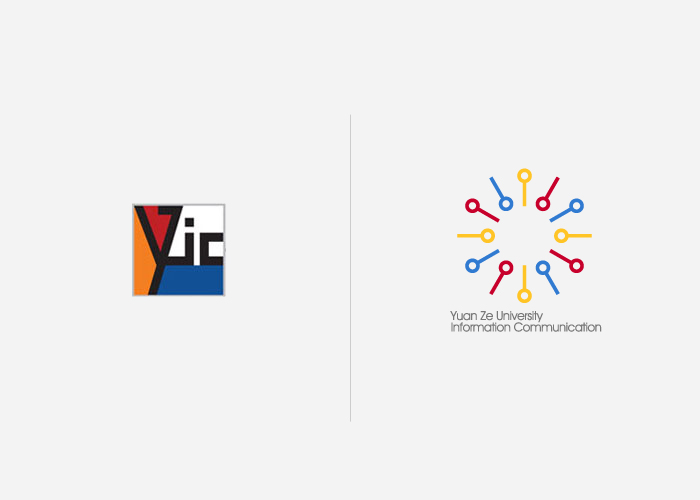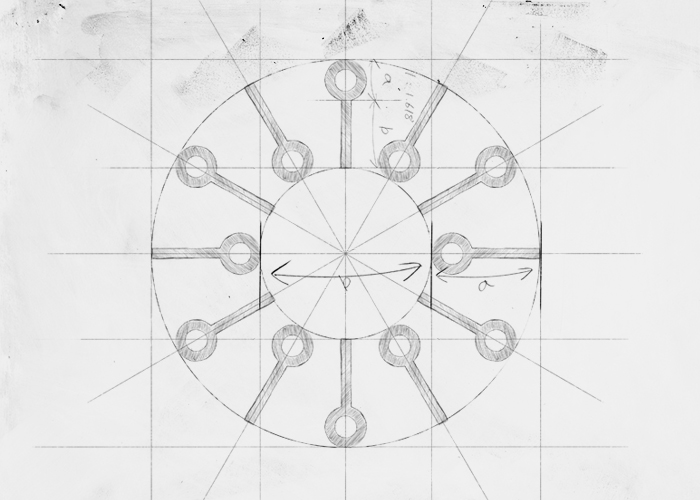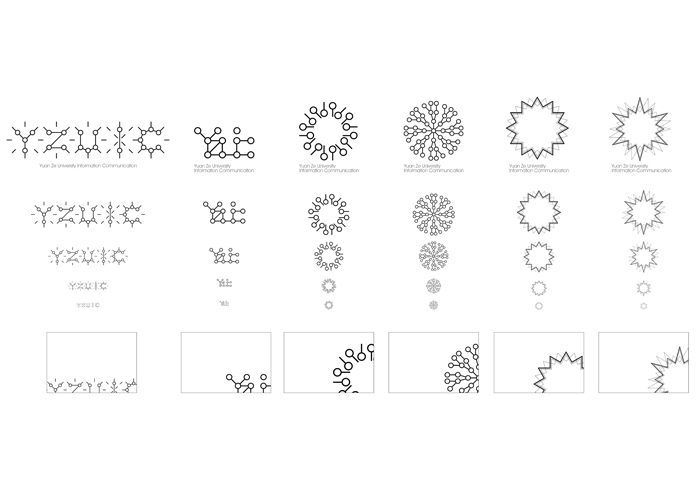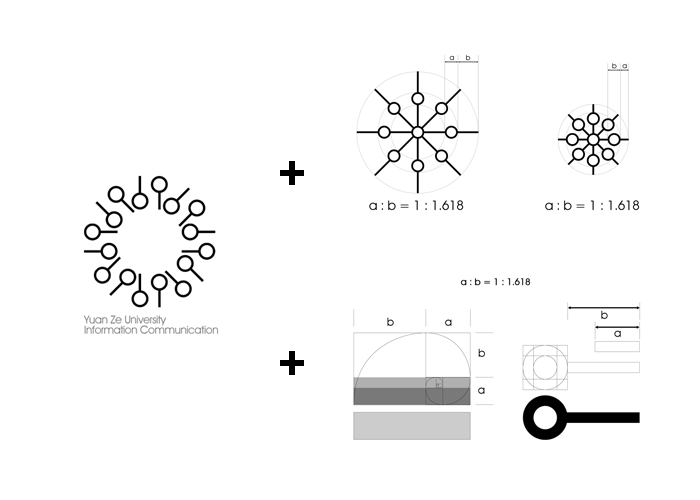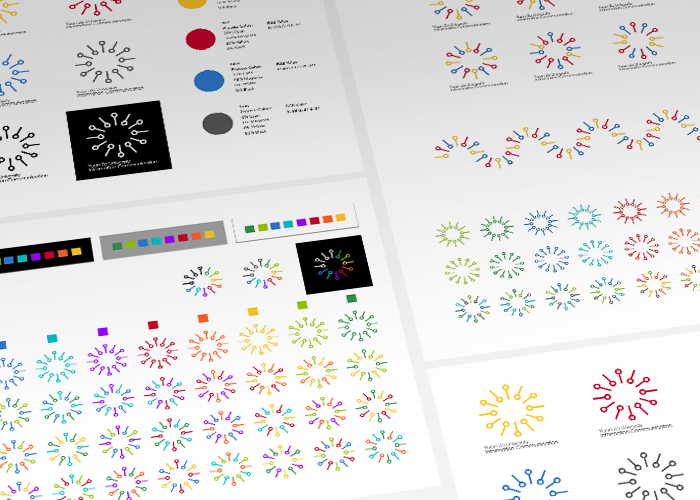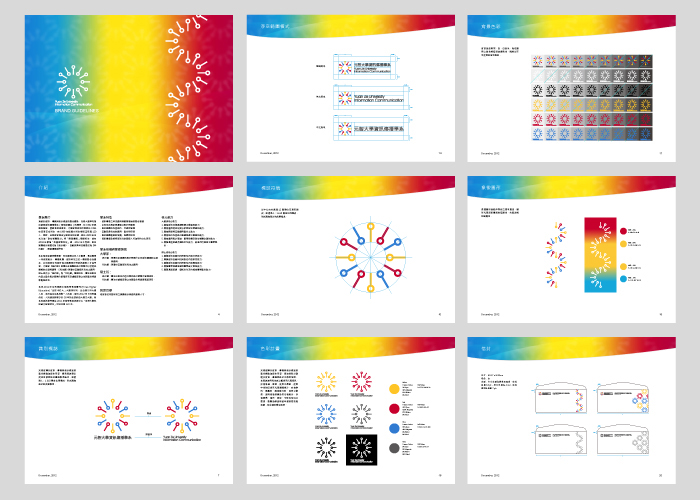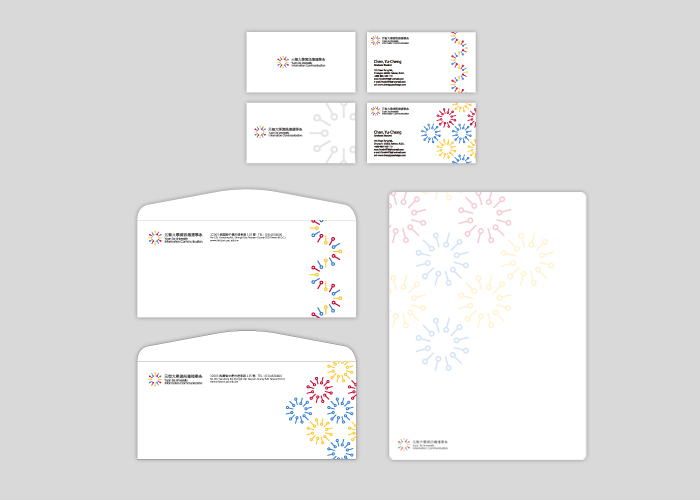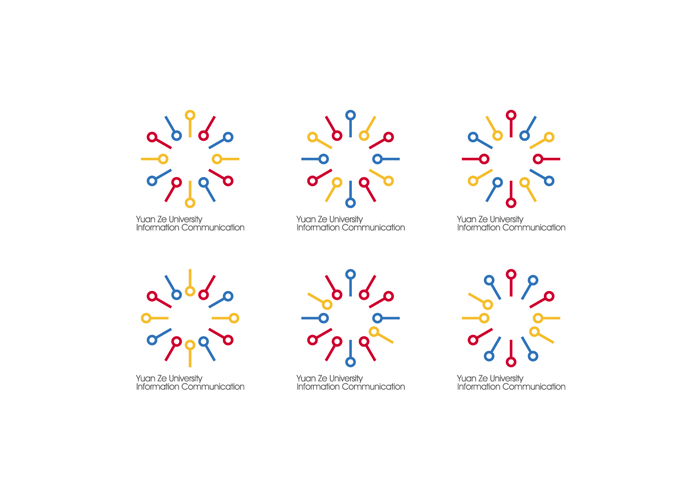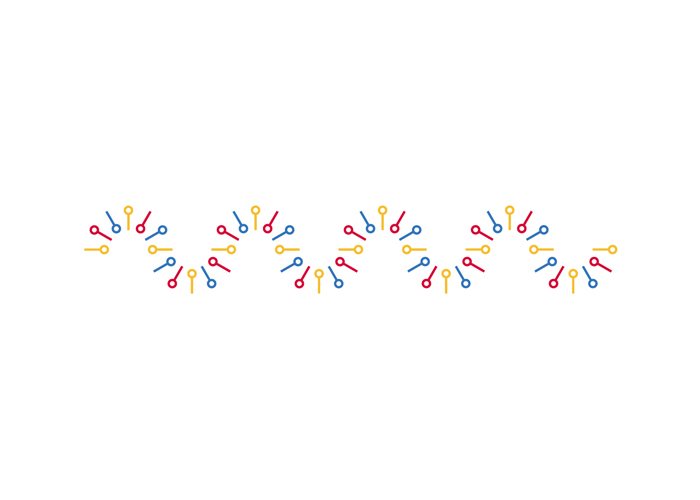
元智大學資訊傳播學系動態商標設計
設計方法與理念:
本創作利用時限性、循環、非固定循環與靜止四種不同時間表現形式,來呈現企業標誌理念。 本創作研究將依照Balmer (2006) 企業識別6Cs概念,分析元智大學資訊傳播學系之理念,標誌設計針對資訊、訊號、傳播抽象概念來發想,識別標誌便以資訊符號與數位傳播概念結合,以結點連結、結點延伸、線條來表示資訊符號之概念,並運用形態、造型、色彩、字型、比例與構成、肌理元素設計。在基本元素構成中,元素的厚度取自於鸚鵡螺殼的結構之比例,標誌的0與1的元素且透過1:1.618 之黃金比例所構成,標誌一以中心向外擴張12個單位元素來組成,象徵孕育全方位之人才。本創作在10種設計樣式中選出6種設計之初稿,並在其中選出2種標誌作為後續標誌製作,選出2種標誌並透過比例原則的概念進行修改。
一、時限性之表現形式在時限性類別中本創作將二個標誌分成三類製作,分別為一般、科技組與設計組,動作方式將採用「描述事件」與「切換」的方式進行,在一般的時限性影片中,本創作將所有動態商標變化結果作集結,讓大眾認識與了解此標誌的動態變化呈現。科技組影片將標誌運用依序漸變生長的方式,來象徵科技不斷成長與進步,並用科技感色彩與效果襯托。設計組注重於概念發想與專業規劃,影片則運用設計的過程來詮釋。
二、循環之表現形式本創作在循環類別中所使用的動作方式採用「旋轉」的方式進行循環,元素所旋轉不同方向會產生不同的形態,象徵轉換方向,產生新面貌。
三、非固定循環之表現形式本創作在非固定循環類別中所使用的動作方式採用「互動」的方式進行,透過研究個案中所使用的概念,將採用客製化標誌進行設計。本創作將標誌區分出科技組為藍與綠色系,設計組為黃與綠色系,由製訂出的7種顏色中搭配標準輔助色彩,各以5種色彩作變換。由於非固定循環需經由讀取資料數據後作變化,來作為本創作的「互動」方式,在第一階段會區分使用者身分為設計組或科技組,在第二階段會索取使用者身分證字號後4碼與學號後2碼,最終產生出使用者專屬標誌。
四、靜止之表現形式本創作在非固定循環類別中所使用的動作方式採用「變形」的方式進行,透過標誌元素的排列與重組,運用於非時間性媒體上。